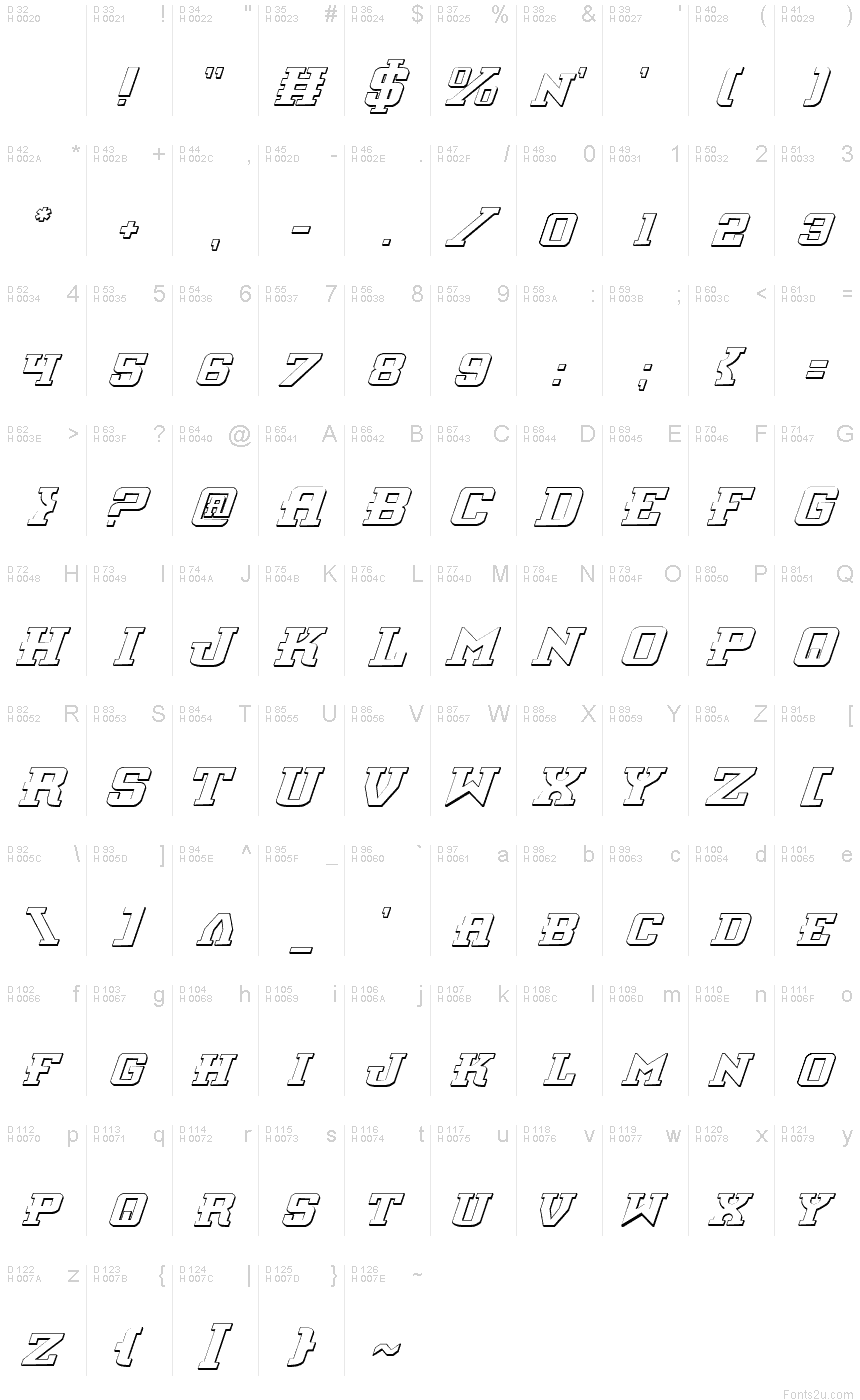
Interceptor Shadow Italic von Iconian Fonts ist eine kostenlose, konturierte, kursive Display-Schrift mit einer dynamischen Note, die an Comics und Sport-Überschriften erinnert. Die Großbuchstaben neigen sich nach vorne, haben eine breite, kantige Form mit abgeschrägten Ecken und eine feine, versetzte Schattenlinie. Das verleiht den Buchstaben eine markante, plakative Dynamik, ohne überladen zu wirken.
Sie passt perfekt für Arcade-Flyer, Team-Logos, Comic-Cover, Titelkarten und kurze Verpackungstexte, bei denen die kostenlose Schrift mit wenigen, großen Worten wirken kann. Nutzen Sie sie für Überschriften, Monogramme oder Cover-Texte, wenn Sie durch den angeschrägten Schatten-Look Geschwindigkeit und Wirkung erzielen möchten.